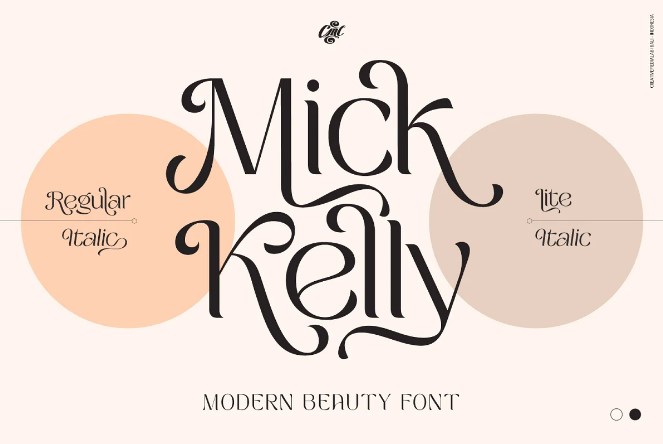
Creativemarket Mick Kelly Font
[Creativemarket] Mick Kelly Font
Mick Kelly засечка красоты с большим количеством уникальных и красивых альтернативных символов, которые вы можете объединить, чтобы получить красивые окончательные надпись с красивыми и динамичными формами всего за несколько секунд!
Этот шрифт подходит для использования во многих дизайнерских формах, например, в журнале, открытке, логотипе, свадебных проектах и многих других. Мы рекомендуем использовать Adobe Illustrator или фотошоп.
Mick Kelly Lite является легкой версией Mick Kelly Regular, для этого стиля, изменяется только в верхнем регистре, мы удалили чередующиеся, чтобы уменьшить размер файла, он будет загружаться быстрее на вашу веб-страницу, когда вы используете этот шрифт для заголовка текста, названия продуктов или с помощью приложений, которые не поддерживают функции OpenType, это очень легко сделать красивые слова, просто набрав и тада... вы закончили.